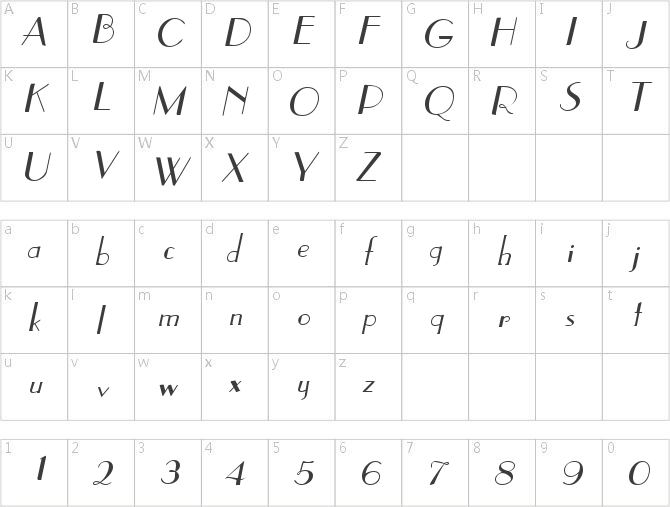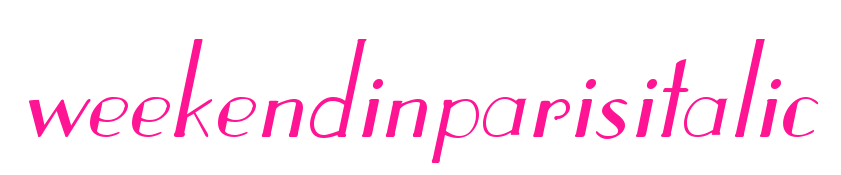
weekendinparisitalic 詳情頁
weekendinparisitalic字體字庫是一款讓人賞心悅目、百看不厭的英文字體,適合各類廣告和產(chǎn)品包裝設(shè)計(jì)應(yīng)用,字體大小0.05MB,格式為ttf字體,上傳用戶是后天的昨天,作者/版權(quán)方為未知